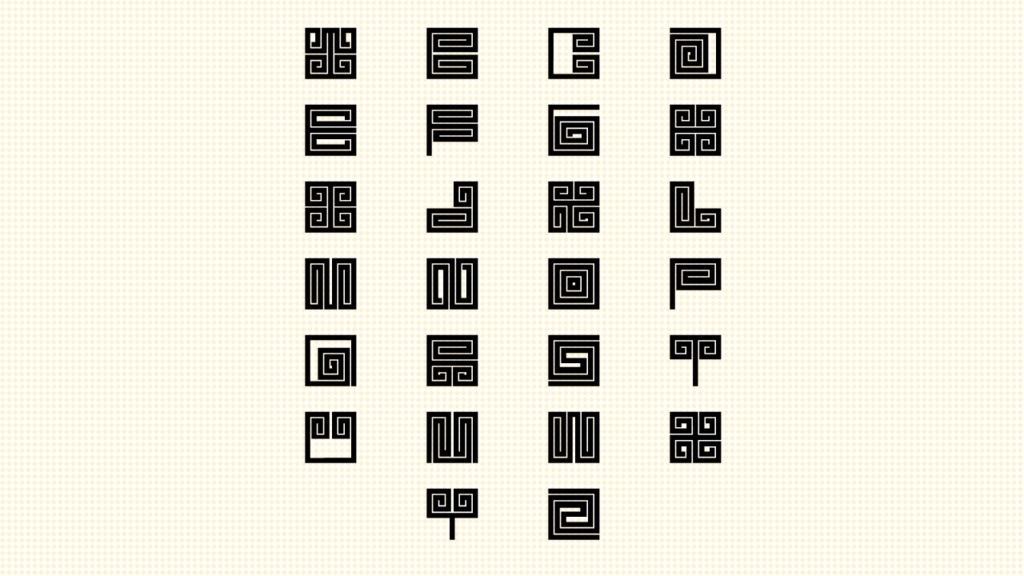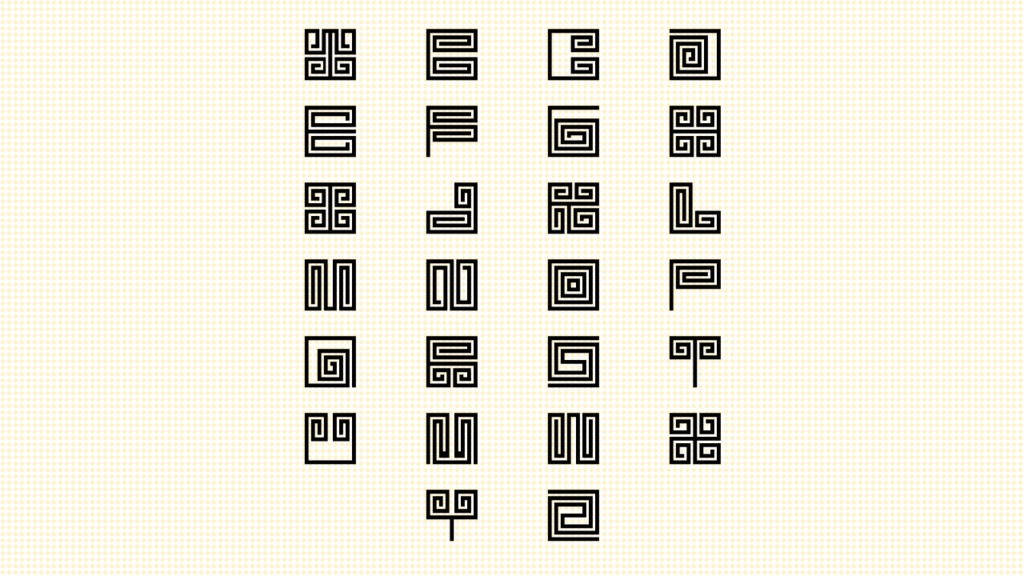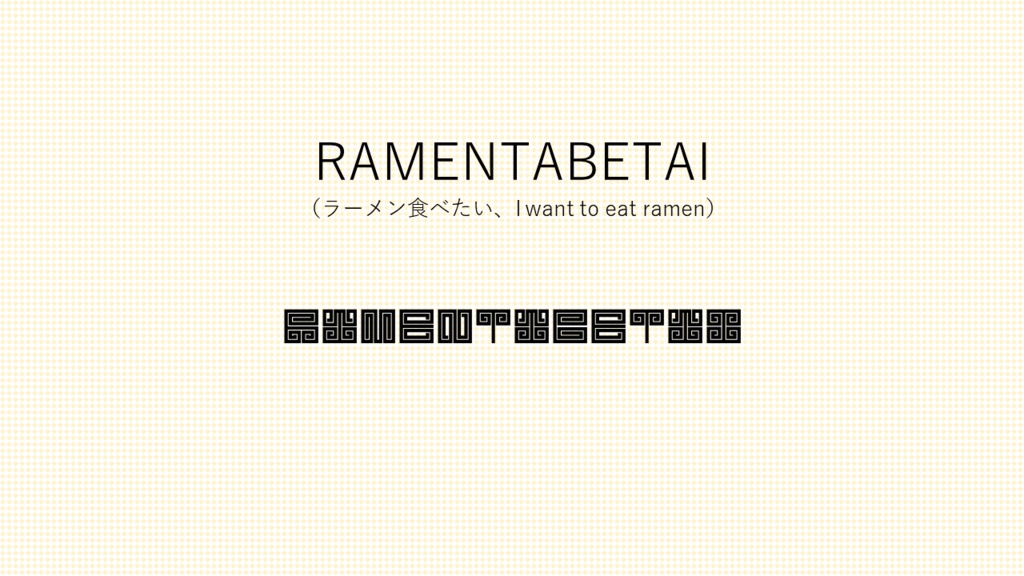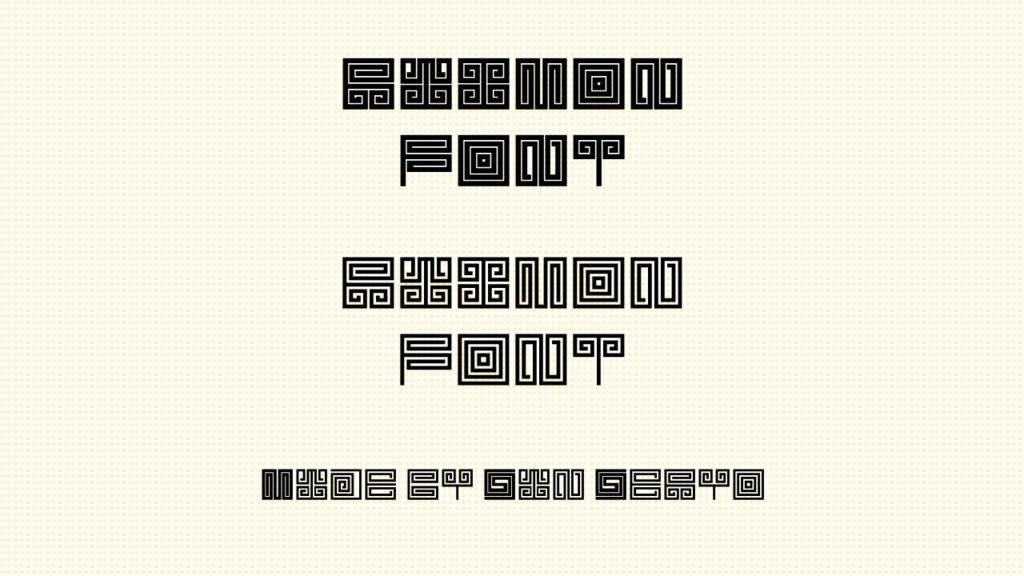
雷紋フォント
雷紋からインスピレーションを得たフォントです。 可読性は低いため、食器や服飾のデザインなどにお使いください。 文字はA~Zまでの26種類で、大文字では太字、小文字では細字となっております。 太字と細字とでは線と空間との比率が異なるため(画像参照)、状況に合わせてご活用ください。 Windows 、Mac それぞれに対応している OpenType および TrueType の雷紋フォントを同梱しております。 ただし、WindowsにおけるOpenTypeしか動作確認をしておりません。 もし不具合などございましたら、お手数ですがご連絡のほどよろしくお願いいたします。 順次、不具合などを修正して更新していく予定です。 このフォントは芹生彡が作製したものであり、著作権は放棄していません。 購入後は複数のプロジェクトに亘って使用可能です。 ご利用に関して当方へ連絡する必要はありませんが、成果物などについてご一報くださると今後の活動の励みになります。 以下の規約の基、ご自由にお使いください。 ▼商用利用可能 ▼自作発言および作者の虚偽の禁止 ▼再配布禁止 ▼アダルトサイト、アダルトゲームでの使用は原則禁止(どうしてもという場合はご相談ください) ▼政治活動での利用を禁ずる ▼犯罪に抵触する可能性のある行為に利用することを禁ずる ▼利用する場合、当該作品内もしくは作品概要欄等にクレジットを明記ください 例:フォント/芹生彡 本フォントを使用したこと、本ファイルをダウンロードしたことにより起こった事象については責任を負いかねますので、ご利用は自己責任でお願いします。 本規約は予告なく変更される場合があります。予めご了承お願いします。 This is Raimon Font. (The raimon mean lightning crests and is similar to Asian Meander.) This font is inspired by raimon. The font is not very readable, so use it for tableware and clothing designs. There are 26 different types of letters from A to Z, bold for uppercase letters and fine for lowercase letters. As the ratio of line to space differs between bold and fine print (see image), please use it according to your situation. It includes both OpenType and TrueType fonts for both Windows and Mac. However, we have only tested the OpenType font for Windows. If you have any problems, please contact us. We are planning to fix the problems and update this site as they arise. This font was created by Serio and the copyright is not waived. Once purchased, you may use it across multiple projects. There is no need to contact us about your use of it, but it would be helpful to let us know about your work, etc., to encourage our future activities. Please feel free to use it, subject to the following terms and conditions. ▼Available for commercial use. ▼Prohibits self-made statements and falsehoods of the author ▼Redistribution prohibited ▼In principle, use of adult sites and games is prohibited (Negotiable). ▼Forbidden to use it for political activities. ▼Prohibits the use of such a device to commit an act that may violate a crime. ▼If you use the work, please credit it in the work or in the summary section of the work. Example: Font/Seryo San. We are not responsible for the use of this font or for any problems that may occur as a result of downloading this file. Please note that the terms of use are subject to change without notice. Please note that they are subject to change without notice.